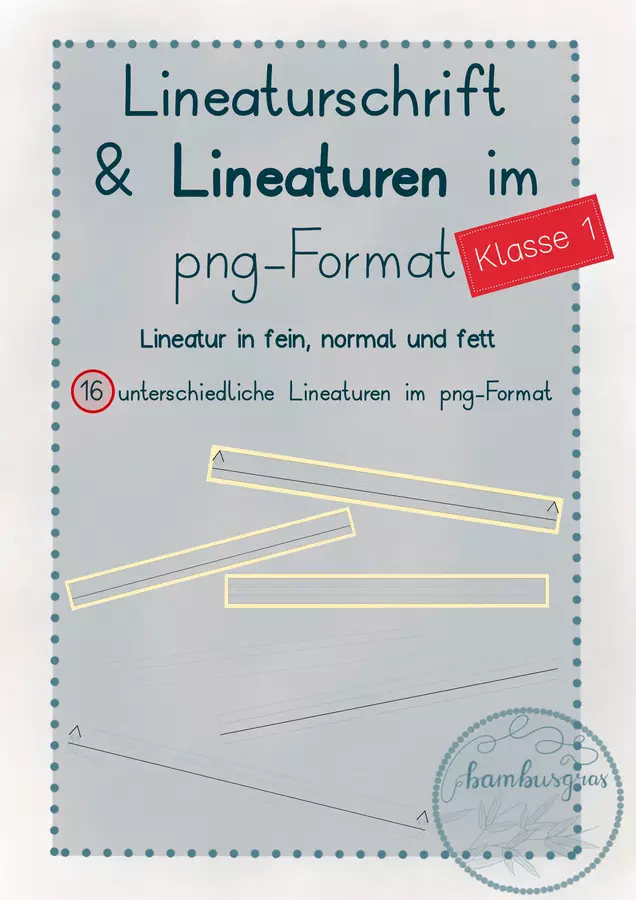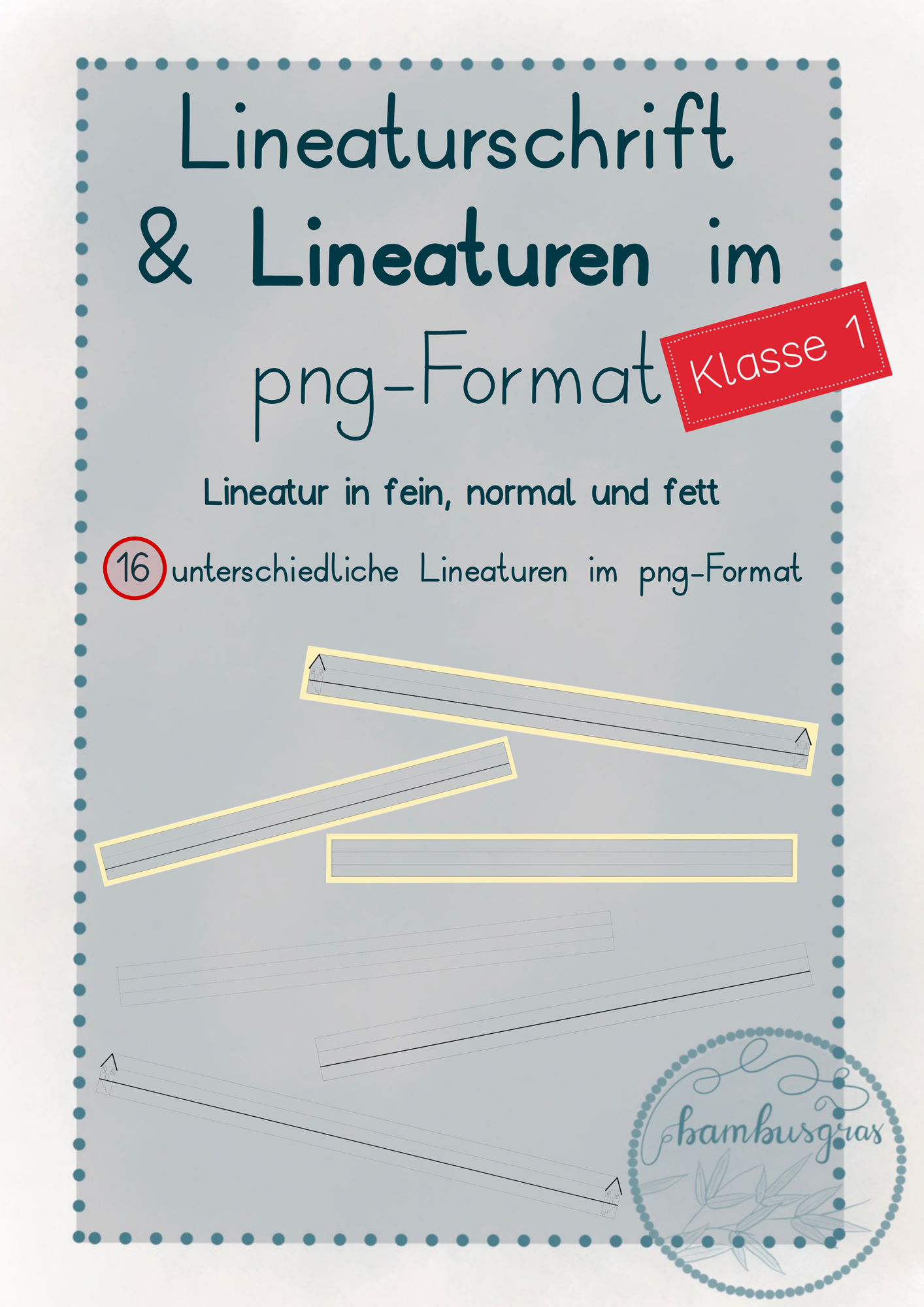
Der Kreativität sind keine Grenzen gesetzt ;-)
Hallo, sind die Lineaturen auch zu kürzen oder sind es immer lange Reihen? Ich suche nach einer Lineatur/Lineaturschrift, mit der ich auch einzelne Wörter in Lineatur schreiben kann... Liebe Grüße!
Man kann sie nur vergrößern oder verkleinern, kürzen funktioniert nicht.